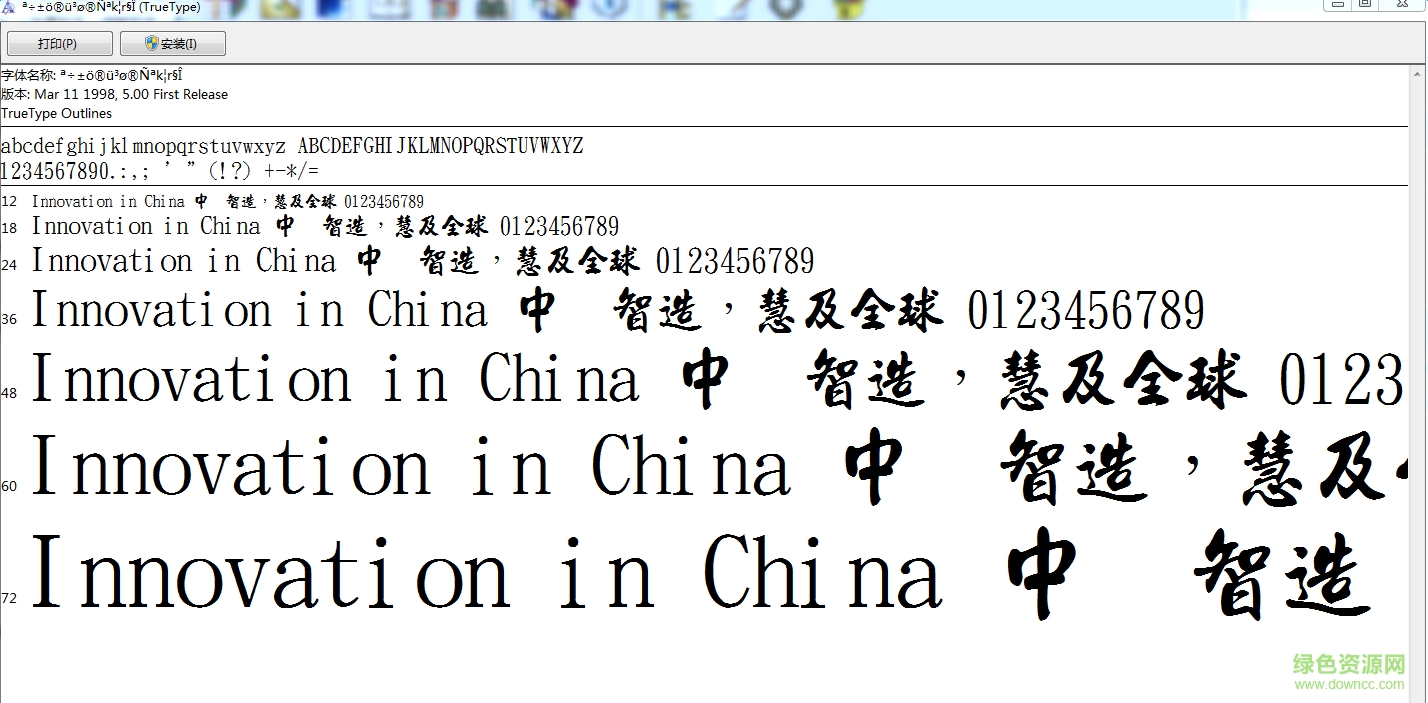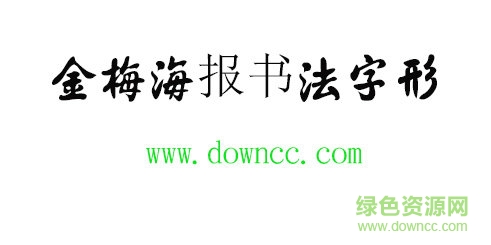
金梅海報書法字形字體是一款金梅類海報字體軟件,書法字形字體給人非常醒目的感覺,深受廣大書法家的喜愛,適用于海報類設(shè)計,非常的具有特色,能讓你的字體設(shè)計比別人的更加出色哦,需要的朋友就請登陸本站下載使用吧!
金梅海報書法字形是一款金梅類書法字形字體,字體效果比較醒目,喜歡書法字形字體的朋友可以下載使用看看效果如何。